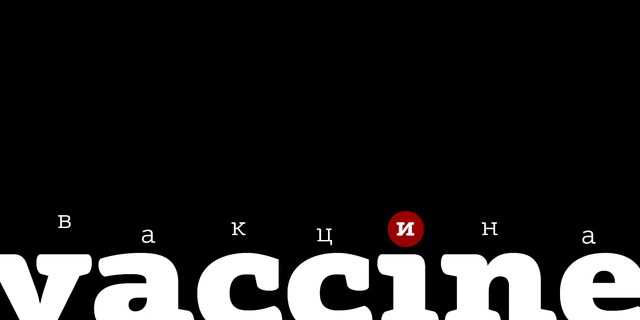
Вакцина (Vaccine) представляет собой брусковый шрифт со смесью обычных и односторонних засечек, то что по-английски можно было бы назвать semi semi slab serif. Засечки, так же как и окончания штрихов, имеют мягкие округлые формы, в то же время места соединения штрихов, наоборот, выполнены жестко. Благодаря такому сочетанию конструкций, шрифт производит впечатление четкого и надежного в наборе и одновременно создает мягкий и доверительный образ. Эта особенность дизайна в сочетании с малым контрастом и брусковыми засечками делает шрифт пригодным для использования в мелких кеглях, в низкокачественной печати и для неблагоприятных условий чтения. Шрифт имеет современный стильный дизайн и неплохо смотрится в ряду модных шрифтов, не теряясь и не смешиваясь с ними. Гарнитура Vaccine включает 10 начертаний пяти насыщенностей с соответствующими курсивами. Она может быть использована практически в любых областях — в журнальном дизайне, рекламе, айдентике, городской навигации, упаковке, детских книгах и.т.д. Шрифт разработан Манвелом Шмавоняном при участии Гаянэ Багдасарян в качестве консультанта. Выпущен компанией ПараТайп в 2013 году.